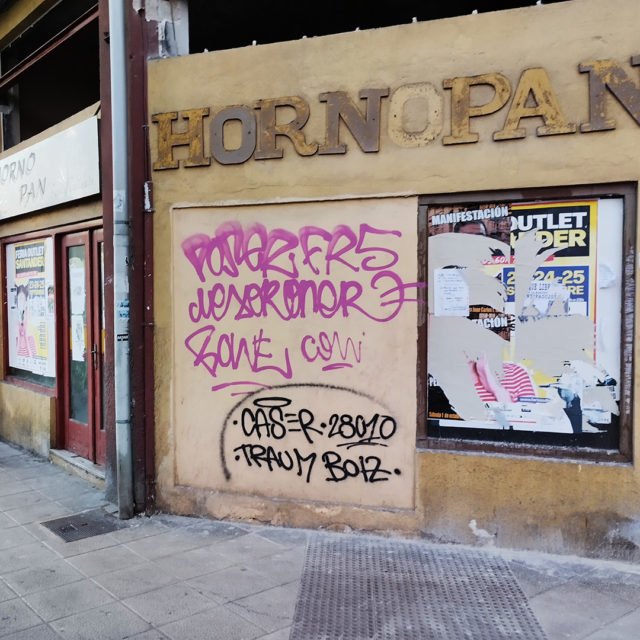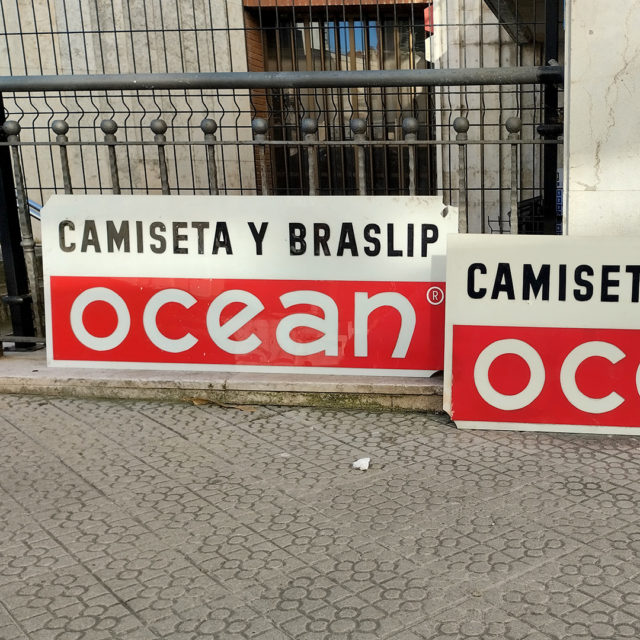
HornoPan y Ocean
Que mejor manera de comenzar el año con colaboraciones, recogiendo estos materiales que se han añadido al archivo del Proyecto y por tanto salvados de su desaparición:
HORNOPAN: Estas letras estaban aún puestas en lo que fue el obrador de HornoPan que había en la calle Marqués de la Hermida, Santander. Gracias a la labor de una Custodia que conoce el proyecto, vio que se iniciaban las obras en el local. Nos avisó de que ya había apalabrado con la empresa de la obra que guardasen las letras. En cuando las bajaron, pudimos recogerlas y depositarlas en el local.
OCEAN: Estos carteles publicitarios de Ocean, que pertenecieron a un rótulo de vela que estaba en la antigua Mercería «La Flor» de Tetuán, Santander.
Han sido donados por César Pombo. Quien fuera propietario de «Regalos Pombo» y que también nos cedió los cristales de su tienda cuando cerró en 2020, es un amante de la historia de comercial de Santander. Publicó en 2015 «Vamos de Tiendas» un libro con fotografías históricas del comercio santanderino, y que para nuestro proyecto es uno de los libros referente por la documentación base que nos aporta en los procesos de investigación.
César, aparte de ser la memoria comercial de la ciudad, es también un colaborador del proyecto y gran custodio. Su hijo Óscar nos acercó el material al local.
Con estos ejemplos, vemos que el proyecto sigue calando en la gente y colabora en la preservación y puesta en valor del Patrimonio Gráfico de nuestra región.
Queremos que los rótulos se protejan y que los podamos ver en la calle, pero mientras llegue ese momento, antes de que acaben en la basura o sean vendidos, mejor guardarlos como parte de nuestra historia.